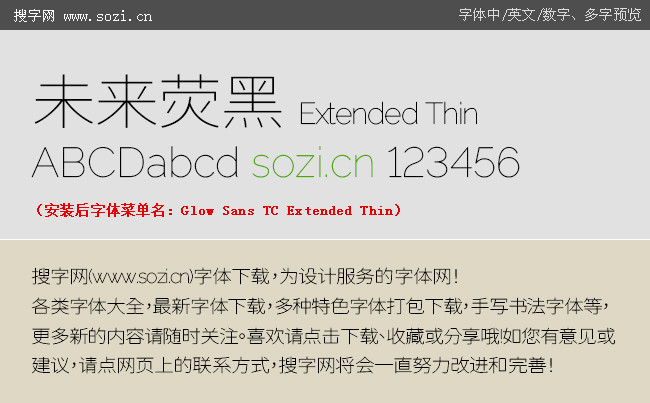
未來(lái)熒黑GlowSansTC-Extended-Thin
搜字網(wǎng)給大家提供一款未來(lái)熒黑GlowSansTC-Extended-Thin中文字體下載,未來(lái)熒黑GlowSansTC-Extended版是未來(lái)熒黑中的一個(gè)寬體系列,未來(lái)熒黑是一個(gè)基于思源黑體、Fira Sans和Raleway的開(kāi)源字體項(xiàng)目,該字體由八種字重,字體中宮與字面更加收斂,細(xì)節(jié)上面處理更加的干練,適合應(yīng)用于藝術(shù)設(shè)計(jì)、平面宣傳設(shè)計(jì)、網(wǎng)頁(yè)設(shè)計(jì)等廣告設(shè)計(jì)。